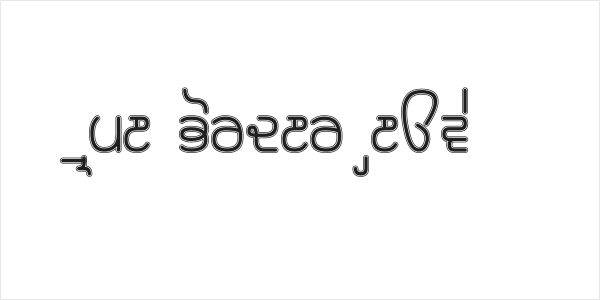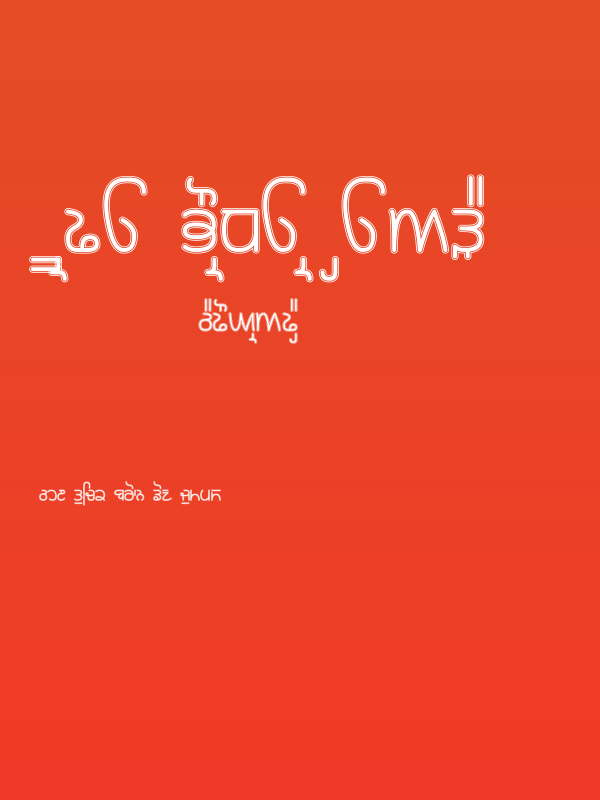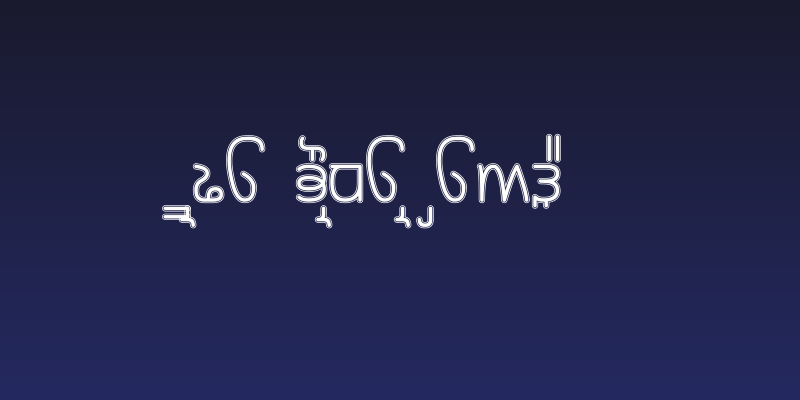
Rupe Border Heavy Font
| Gesamtstil | Modern, Decorative |
| Vorgeschlagene Projekte | Ideal for posters, logos, headlines, and any design project that requires a bold and eye-catching typeface. |